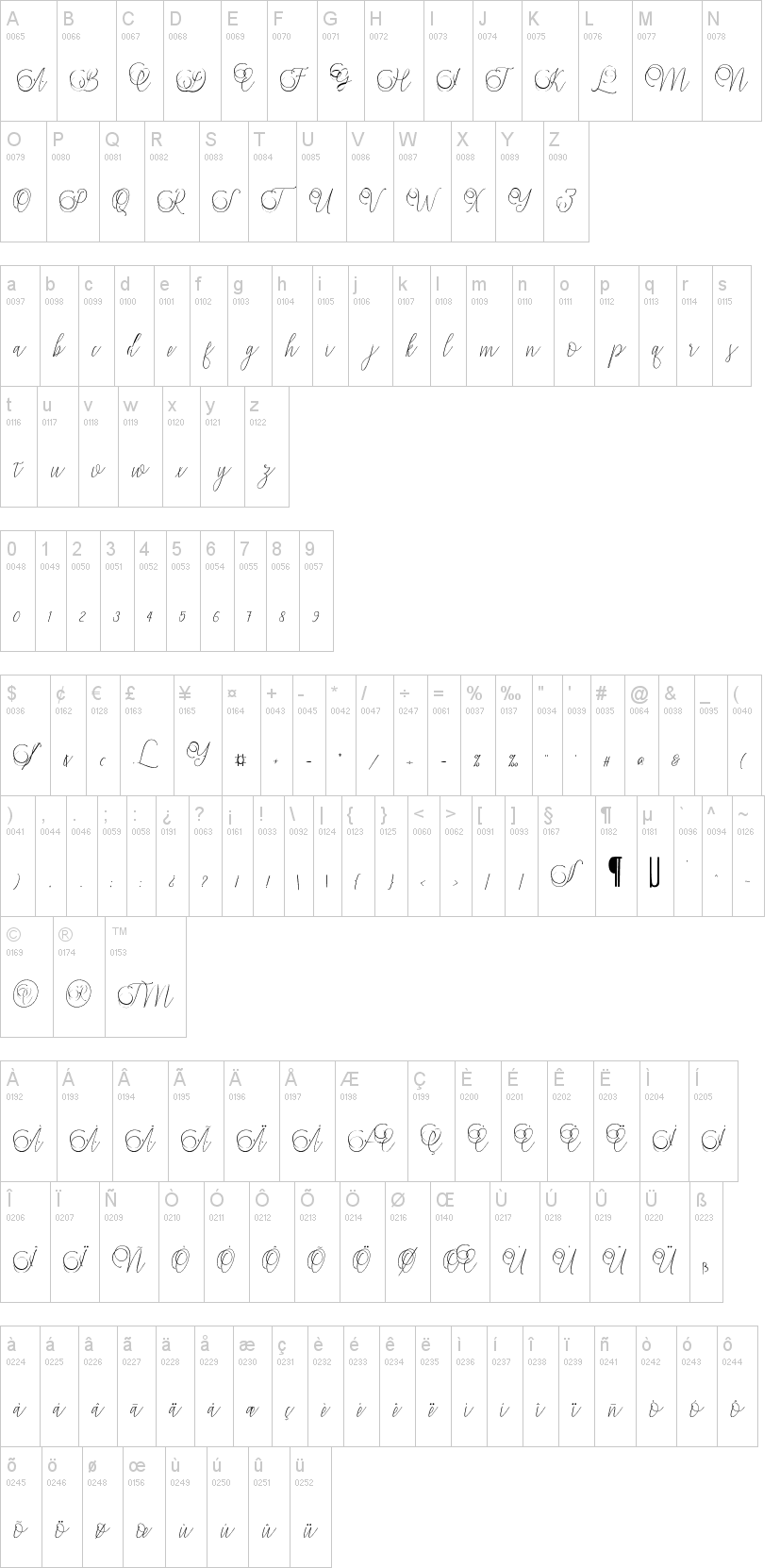
Mandailing 字体是一种基于拉丁字母的字体,源自于印度尼西亚苏门答腊岛的曼达林族(Mandailing)语言。这种字体主要用于印度尼西亚苏门答腊地区的曼达林族传统文化和印刷业。它是一种美观而富于个性化的字体,具有独特的形态和特征,可以识别其源于曼达林文化。 Mandailing 字体的特点包括: 1. 每个字母都有精细的曲线和细节设计,呈现出优雅和美感。 2. 字母间距较窄,紧密排列。这种排列方式使得文本在阅读时更加紧凑,易于理解。 3. Mandailing 字体的字母看起来都非常相似,但是它们的形态各不相同。每个字母都具有独特的形态和特征,从而使得整个字体更加生动和有趣。 总之,Mandailing 字体是一种非常漂亮和有独特风格的字体,被广泛应用于曼达林文化和印刷业。内容介绍
Mandailing是一款非常不错的手写艺术字体,具有很好的视觉感,适合于文化类的宣传设计、商业类品牌的广告和产品包装设计以及个性化文字排版等较多场景。